淘宝、京东等购物网站一年会推出很多活动,例如淘宝出游季啦,最近即将迎来的6.18购物节啦,双十一、双十二这种购物盛会。作为设计师为了设计横幅广告免不了头疼,因为广告在页面中所占的比例较小,一定得设计得醒目,吸引人。小编今天就要为大家解决这个烦恼,给推荐3款集创意与设计于一身的字体。
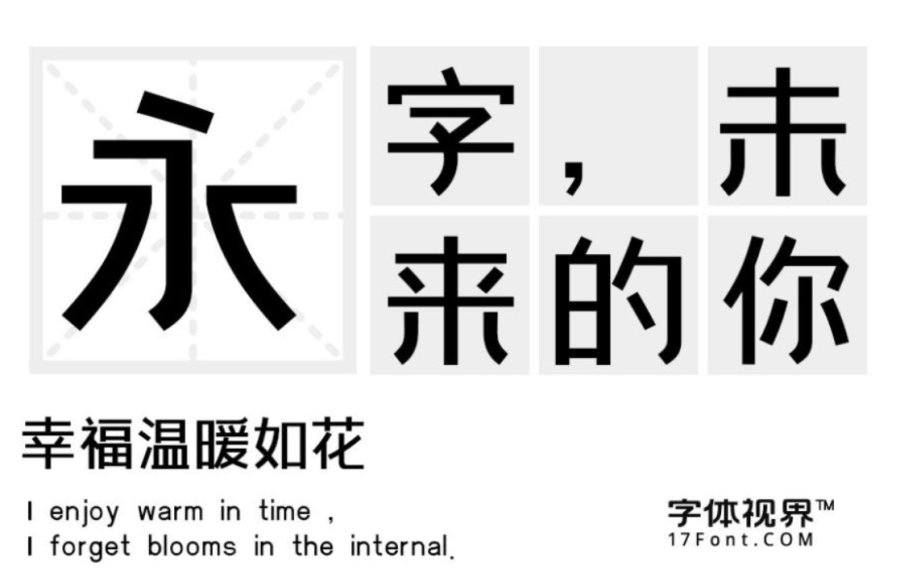
上首文正体:首文正体结构方正大方,线条流畅,简化字体笔画中的钩,转角做圆化处理,为此套字体亮点,横竖笔画大小统一,严谨、有力,作为banner字体简洁大方,一语中的易于看图片识别字体,使得整体设计看起来质感高级,使用率非常高,深受设计师们的喜爱。
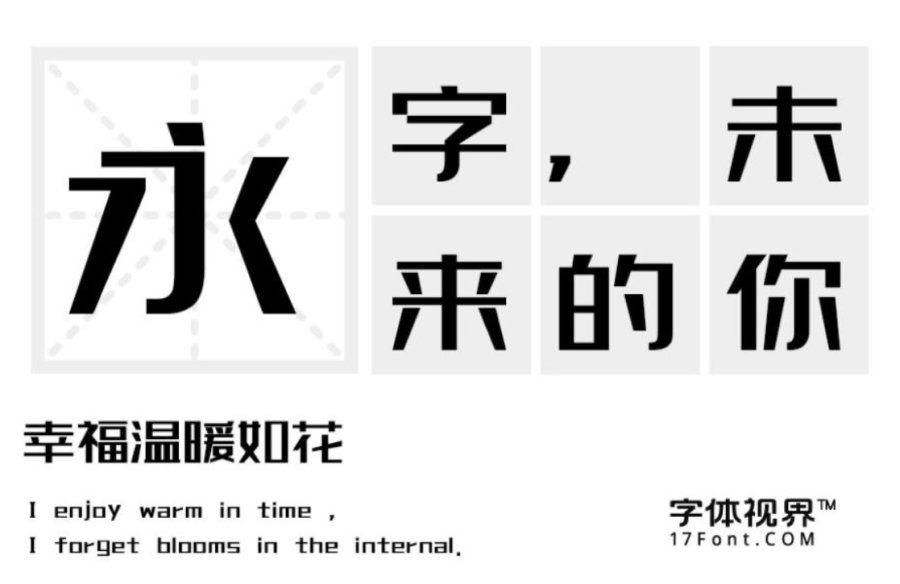
上首京东体:上首京东体方中带圆,上细下粗,转折圆滑,是此套字库的亮点。字库整体特征圆柔、轻巧,时尚。风格清新随意不会过于庄重,适合食品类、服装类、饰品类、化妆品等类型的活动文案字体。
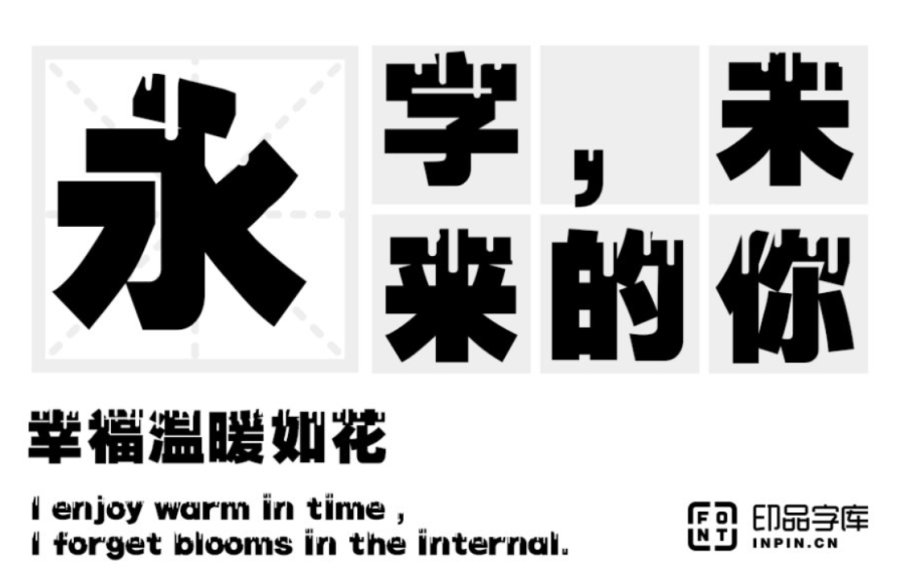
印品油漆体:这款字体在字形设计上采用了"超粗黑体"的基本笔形,参以油漆的创意、形态,婉转有度,于传统美中见时代气息。创意感十足、醒目吸引目光,使用在家装类、科技电子产品类、创意用品等商品活动文案极为合适。